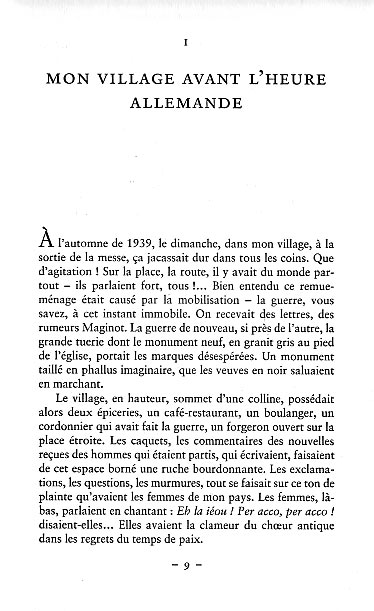
Pour l'anecdote, l'I.N. n'a pas toujours préconisé l'accentuation du A. Il y a une vingtaine (?) d'années, son lexique préconisait l'accentuation des majuscules, à l'exception du A, pour des raisons d'esthétique (je n'ose pas les guillemets, n'étant pas absolument sûr de la citation, mais je suis certain de son sens général).
Une majuscule non accentuée recevant le sacrement de l?accentuation devient une capitale accentuée.
Objet : Re: [typo] ÉricAinsi, cette discussion concernant l'accentuation des majuscules continue (avec confusion entre majuscules et capitales). La manière même dont tout cela se passe, envers et contre toute approche rationnelle, montre que, chez certains, cet acharnement tient plus de la foi religieuse ou de ses substituts que de la recherche sereine de la vérité.En fait, tout cela est le résultat de l'intrusion par osmose de la pensée du monde réformé qui, par le biais de l'anglais, tantôt induit, tantôt renforce une compulsion puriste (ordre, propreté, symétrie, et ce qui y correspond après transposition dans tous les domaines, dont la typographie). Ce n'est pas un hasard, que les Canadiens francophones, qui sont aux premières loges pour ce qui est de la « pression osmotique » du monde anglo-saxon, soient aussi les champions de l'accentuation des majuscules !Jacques Melot